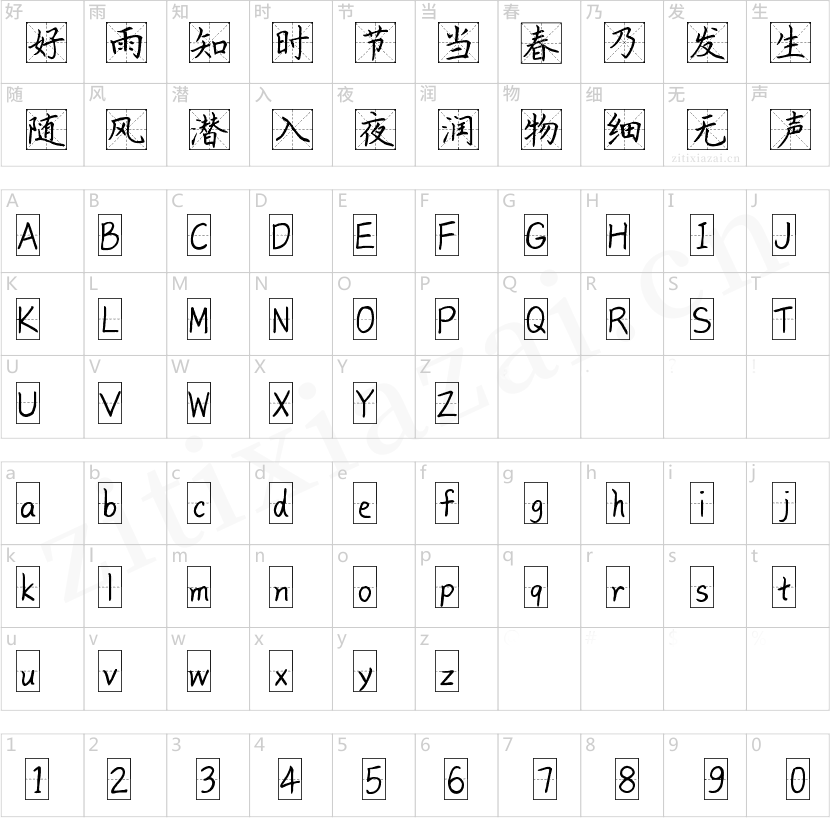
Aa胖格体
Aa胖格体字体
Aa胖格体是一款非常具有艺术性的字体,它的设计灵感来源于对古典艺术的研究,同时又融入了现代字体设计的元素。字形优美,笔画粗细变化自然,给人以大气、典雅的感觉。Aa胖格体是一款既传统又现代的字体,它的设计充满艺术感,美观大方,实用性也非常强。无论是对于设计师还是对于普通读者来说,都是一种非常不错的字体选择。Aa胖格体适合用于具有艺术感的场合,比如海报、宣传单张、书籍封面等。由于其字形流畅且具有动态感,也适合用于大量的文本排版,如报纸、杂志等。